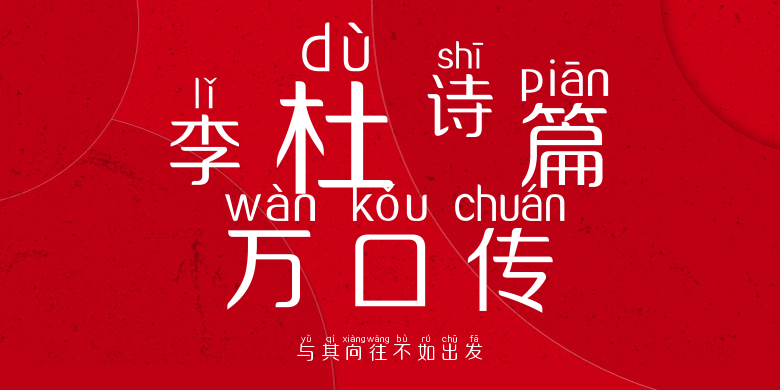
与其向往不如出发
与其向往不如出发,这款字体结构工整、笔画清晰,兼顾美观与易读性,适用于标题、正文、海报、包装、LOGO 等多种场景。字形优雅稳定,风格百搭耐看,适配日常排版与创意设计,让文字呈现更舒适、更具质感。与其向往不如出发一笔一画,皆是细节,以均衡的比例、流畅的线条打造舒适视觉体验,字形端正大气,风格简约现代。无论是商业设计、品牌宣传还是日常排版,都能轻松驾驭,让文字更有格调与力量。与其向往不如出发字体下载。